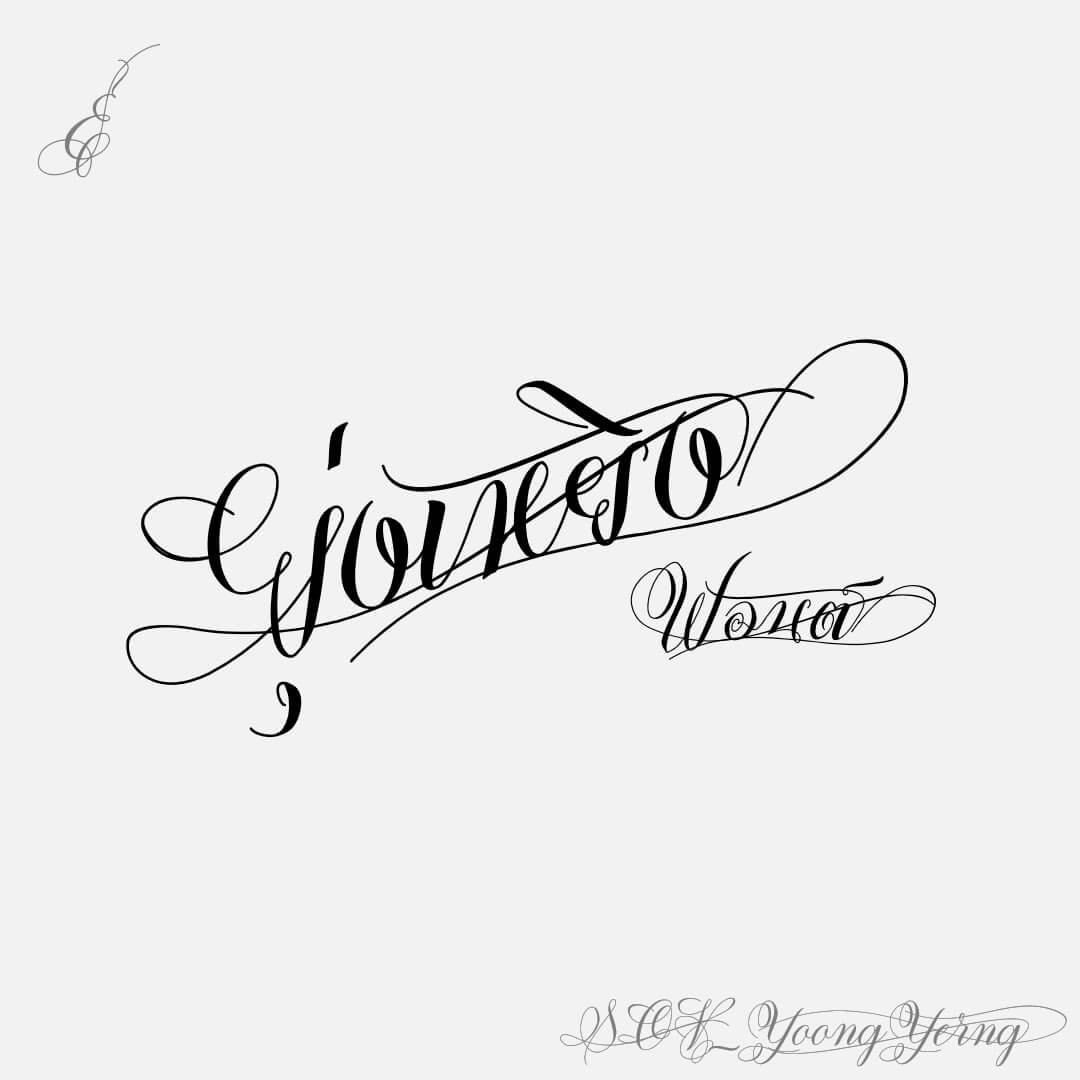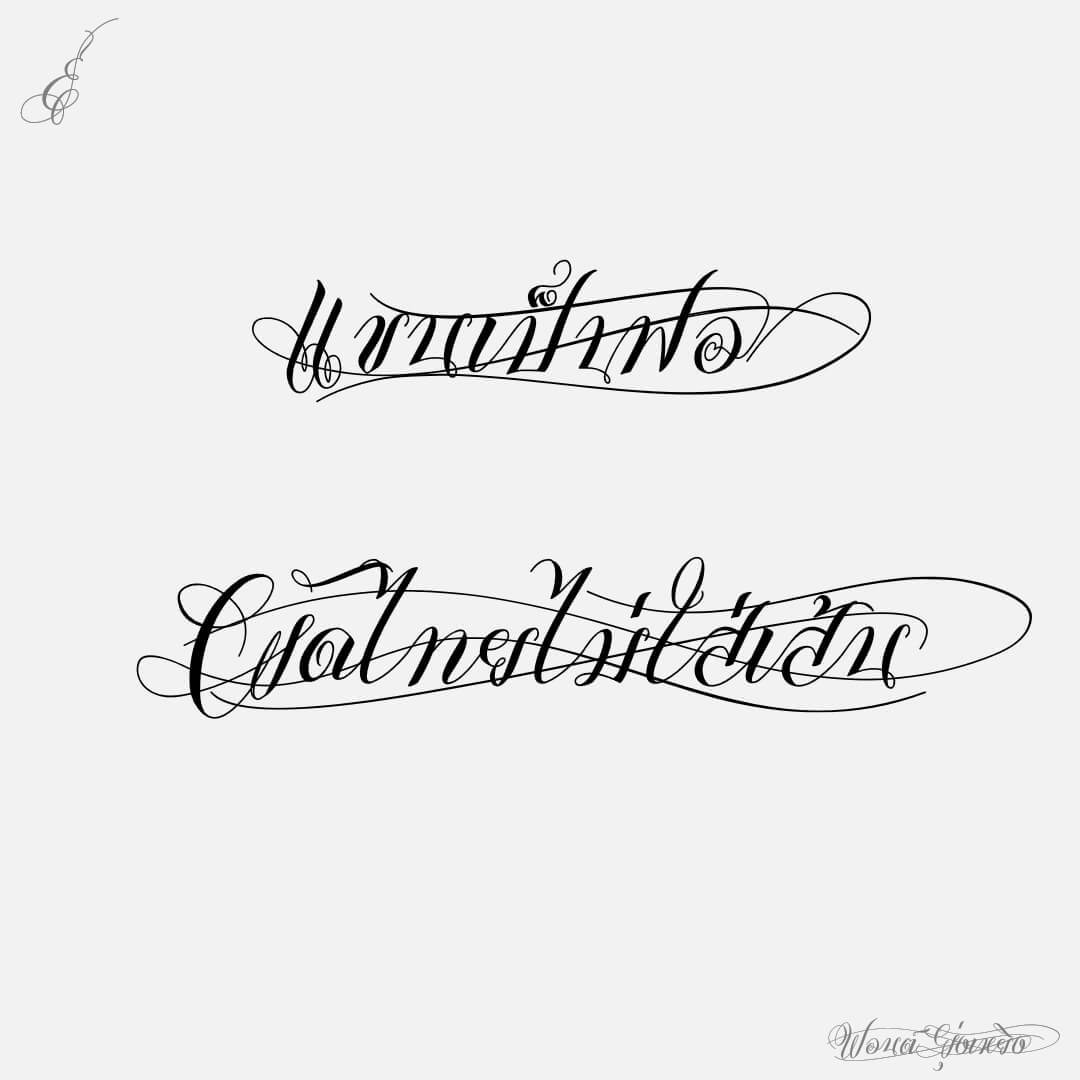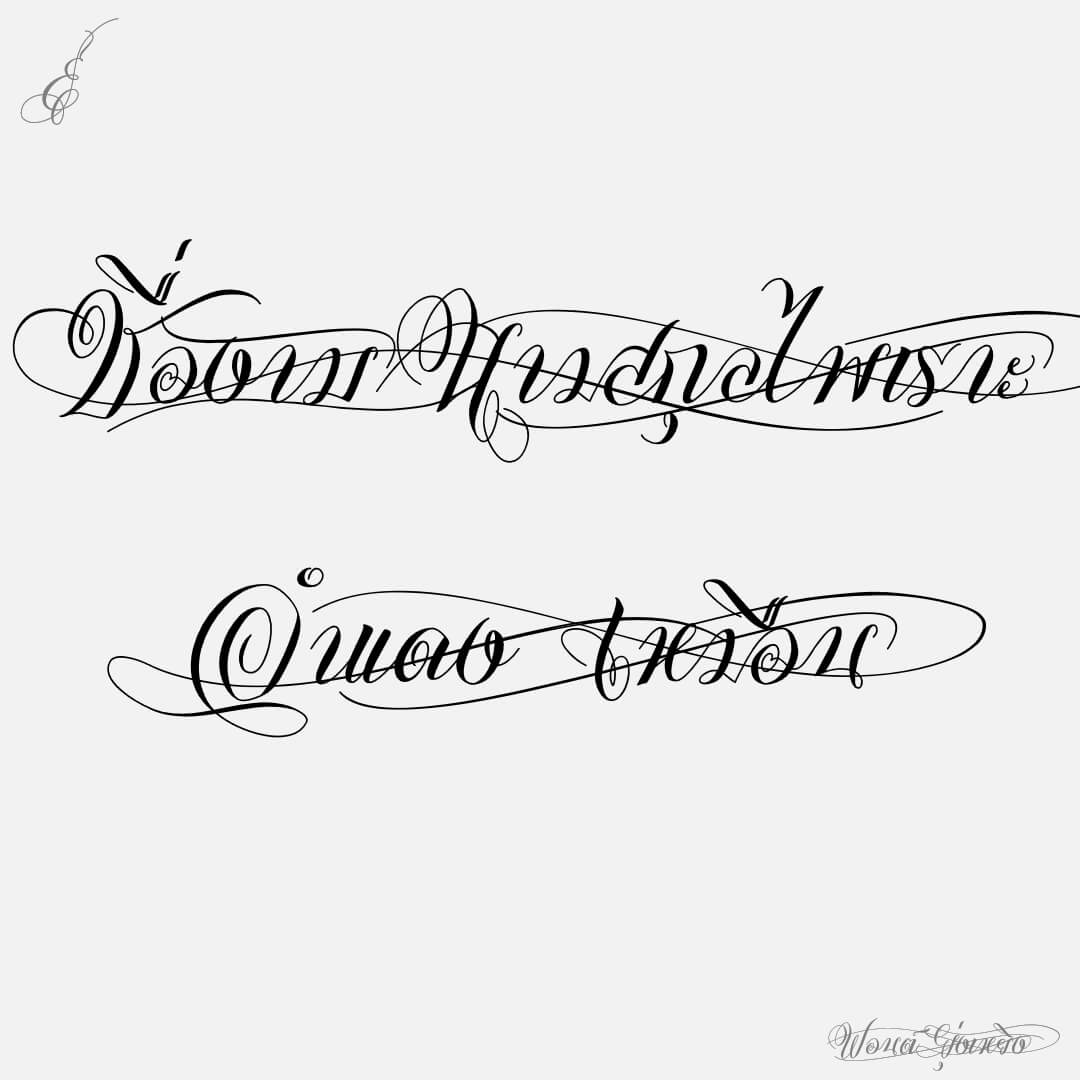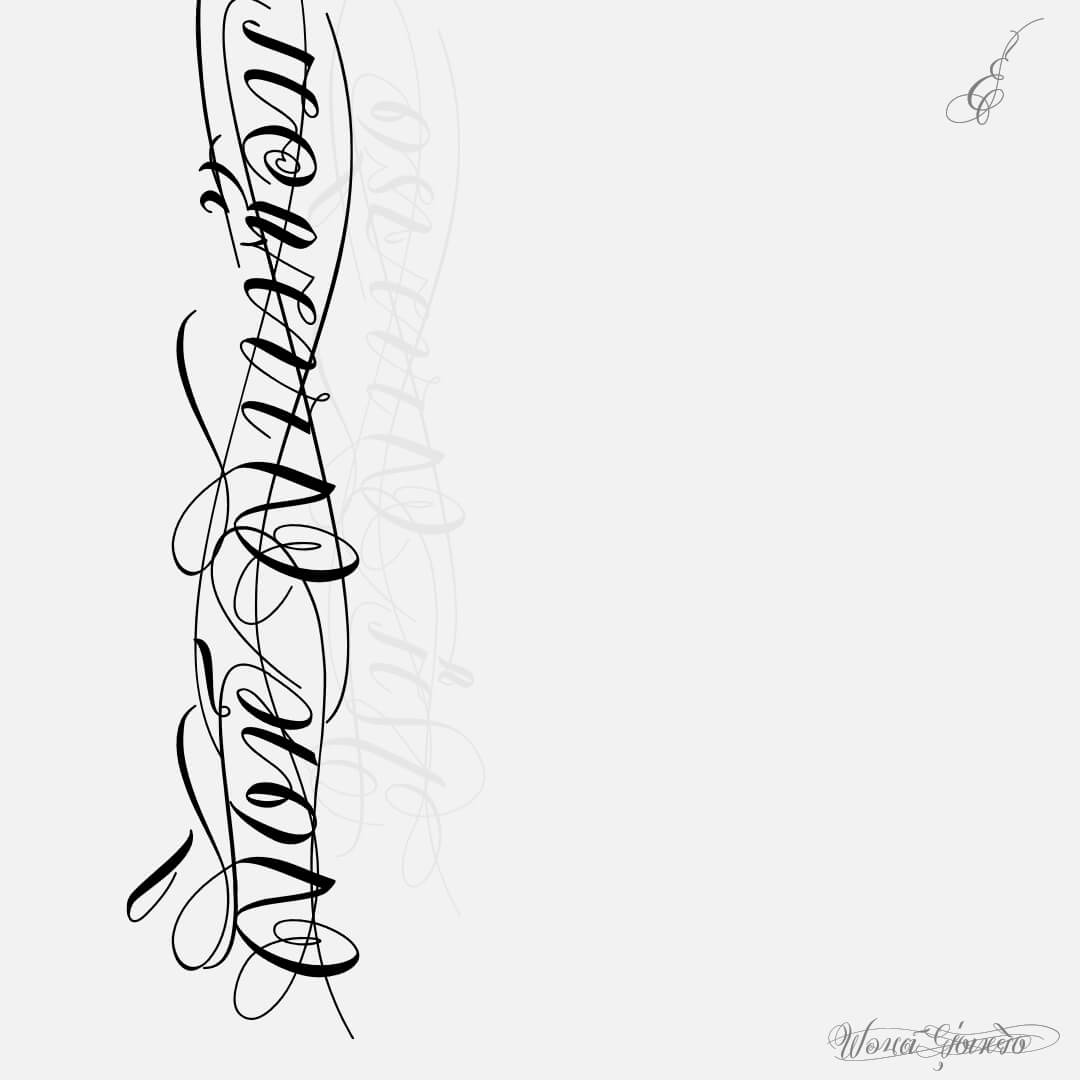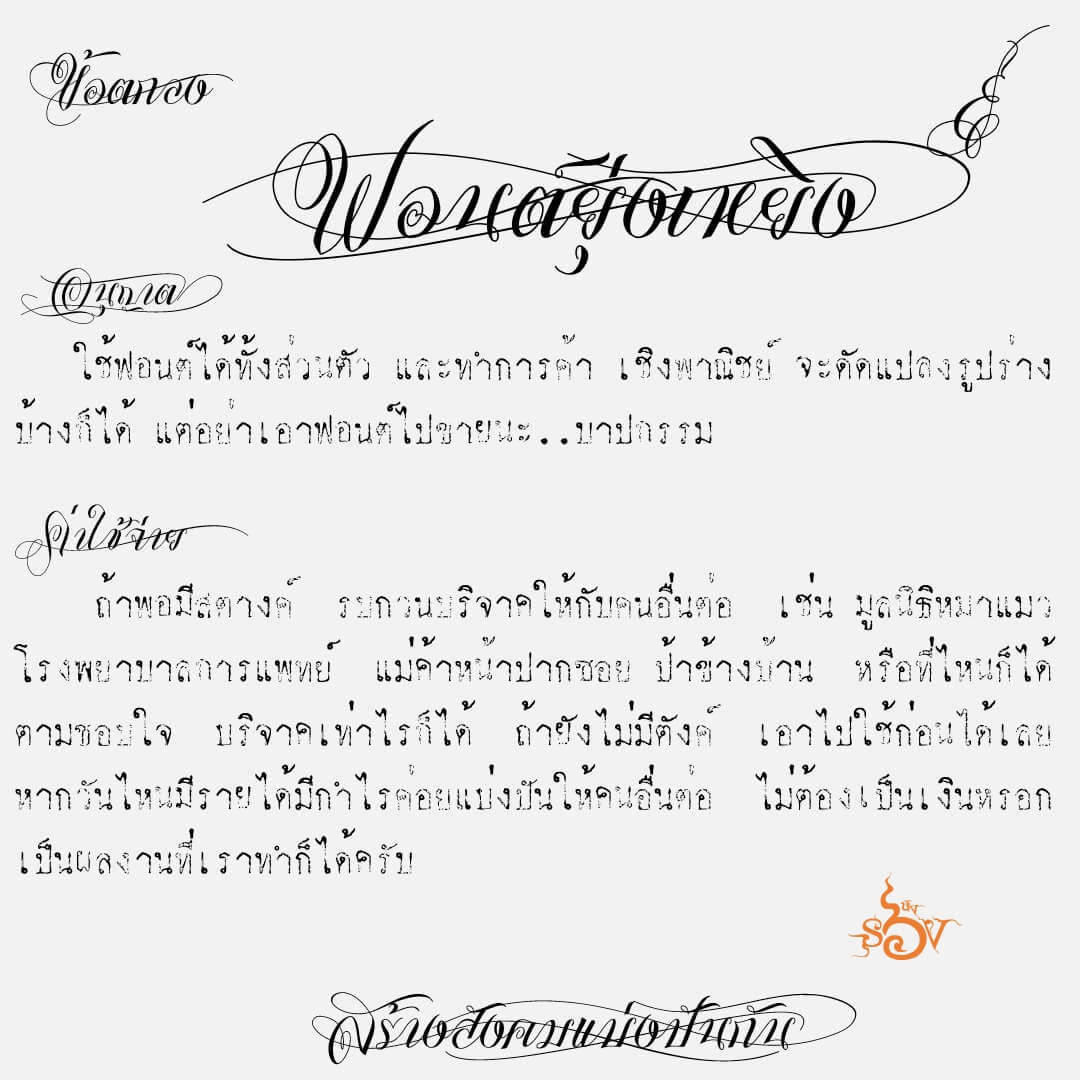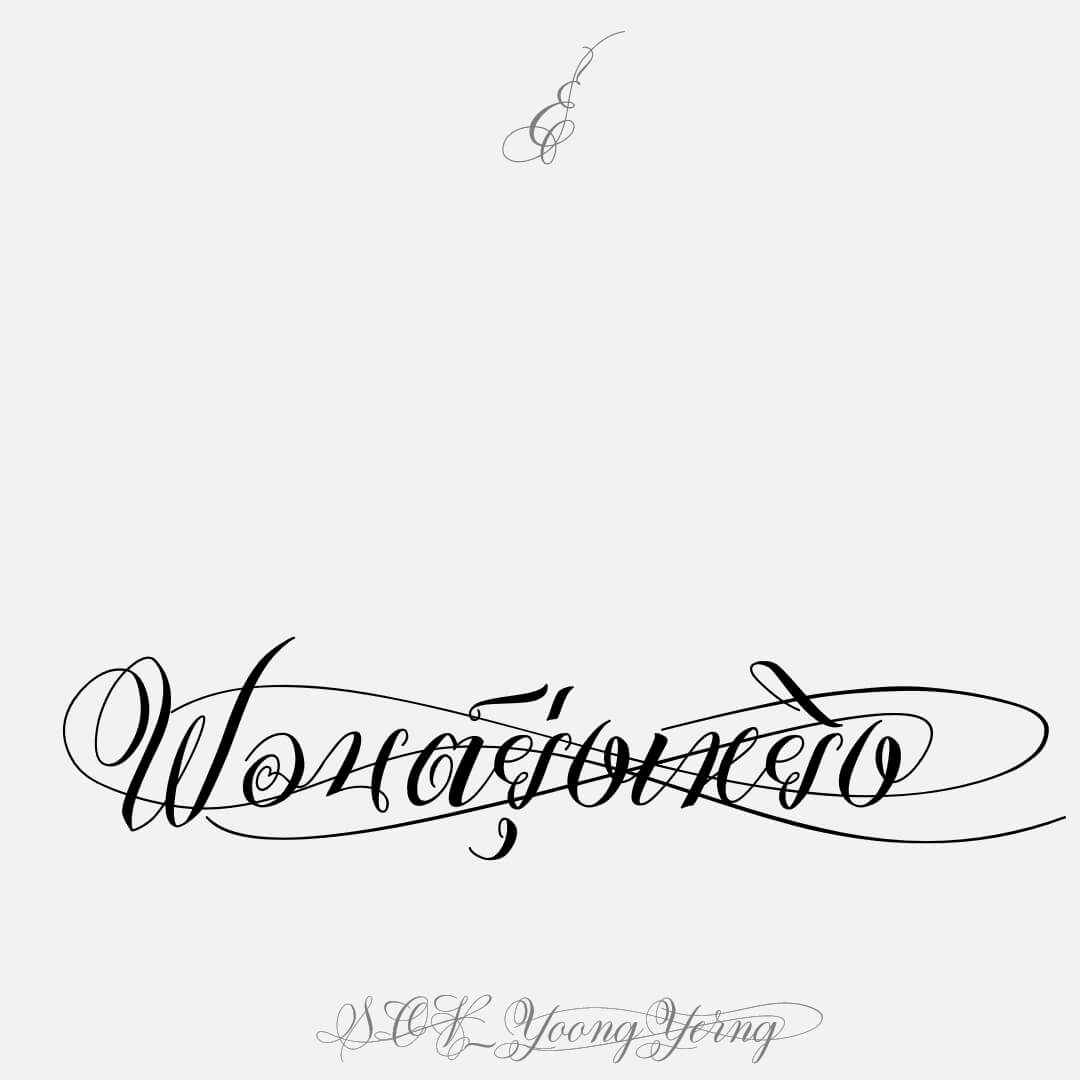
ยุ่งเหยิง – ฟอนต์แนว traditional calligraphy ที่เอามาปรับให้ได้อารมณ์วุ่นวาย… วิธีใช้งาน คือเพิ่มวงเล็บแบบต่างๆ ( ) < > [ ] { } ตกแต่งตามความชอบใจ
เบื้องหลังการออกแบบ : ฟอนต์ ยุ่งเหยิง
ยุ่งเหยิง (SOV_YoongYerng)